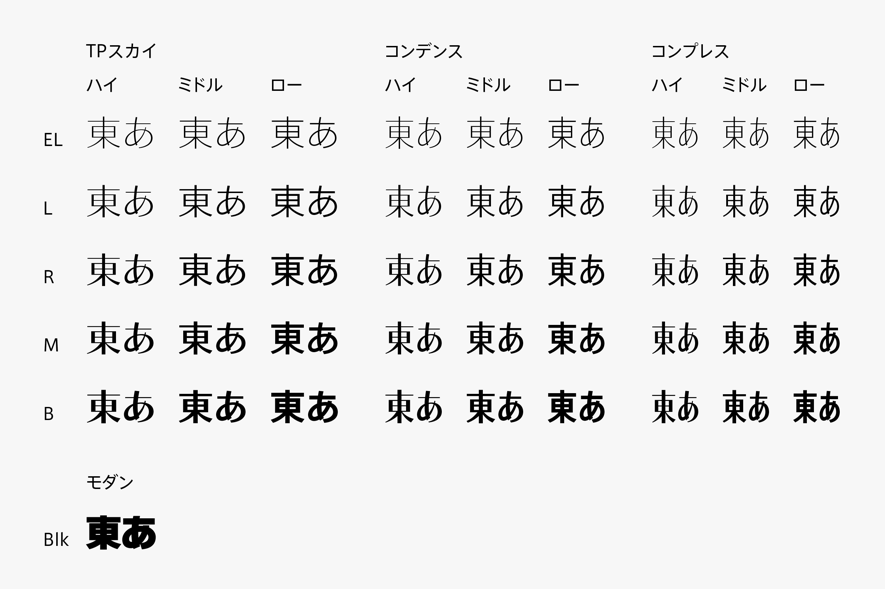
タイププロジェクトが極太ウェイトの「TPスカイ モダン Blk」を発表。TPスカイにモダン書体のカテゴリーを追加して46書体のファミリーに拡張
タイププロジェクトは、スクリーン表示に最適な「TPスカイ」ファミリーに新たに極太のウェイトである「TPスカイ モダンBlk(ブラック)」を追加したことを2020年12月1日に発表した。
2017年4月に発売を開始した「TPスカイ」は、サンセリフ体のストロークに抑揚を与え、単線では表現できない楷書的な筆勢を取り入れた書体で、ウエイト・コントラスト・字幅の3つの軸を持つ初めての日本語フォントとなる。
新たに加わったモダン書体のカテゴリーの「TPスカイ モダンBlk」は、TPスカイのふところ(筆画内の空間)を広くすることで、極めて太いウエイトを実現した。直線と曲線の対比を強くし、筆画をより長くして骨格を大らかにすることで、太さと視認性を両立している。
▼TPスカイ モダン Blk
TPスカイ モダン Blk」は、画数に違いのある文字を並べた際に整って見えるよう調整し、仮名や欧文、画数の少ない漢数字などは、TPスカイ ローコントラストBの1.5倍前後の太さにしている。また、画数の多い漢字では、主要な筆画を太く、他の部分を細めに扱うことで潰れや黒みのたまりを回避し、画数の少ない文字と密度のバランスを取っている。
タイププロジェクトの代表取締役である鈴木功氏は、「TPスカイは、スクリーン表示やデジタルサイネージでの使用を想定した書体ファミリーなので太いウエイトはボールドまでに留めていましたが、フィットフォントサービスによるカスタマイズで、太い欧文に合わせる機会がありました。そうした状況に対応するため、TPスカイのふところを広くすることで、極めて太いウエイトを実現したのがTPスカイモダンBlkです。TPスカイモダンBlkの提供により、フィットフォントでカバーできる領域が格段に広がります。また、ゲームなどのエンターテイメント領域で、強いインパクトが求められる場面での活躍も期待できるフォントだと思っています」とコメントしている。
*TPスカイファミリー:ウエイト・コントラスト・字幅の3 つの軸を持つ初めての日本語フォント